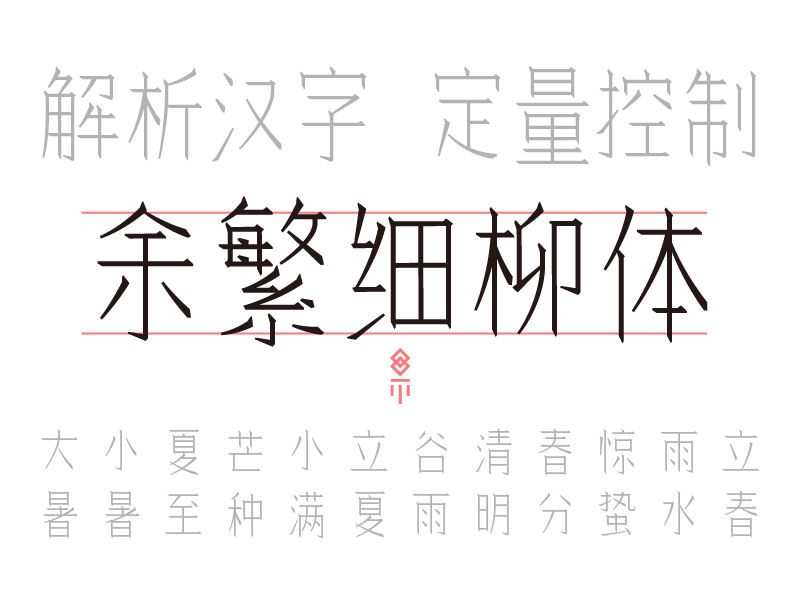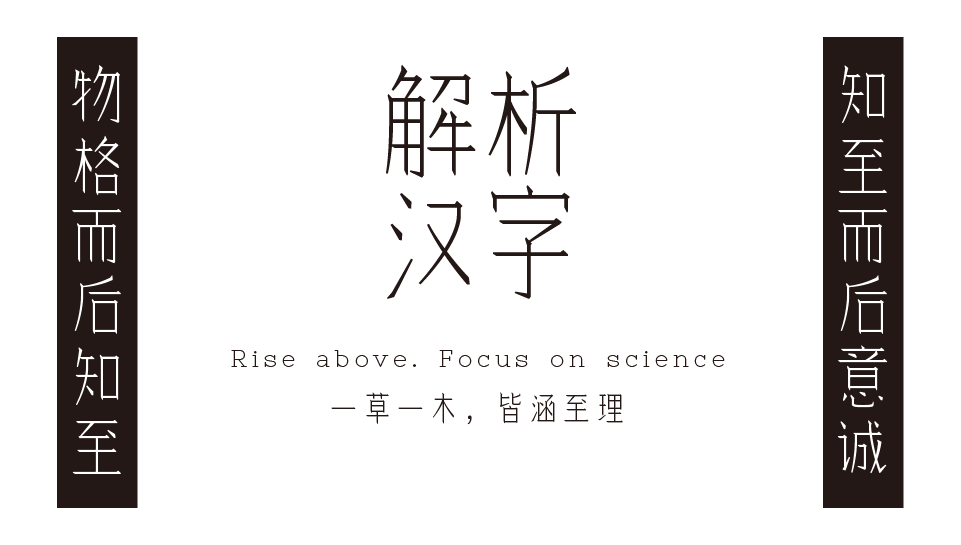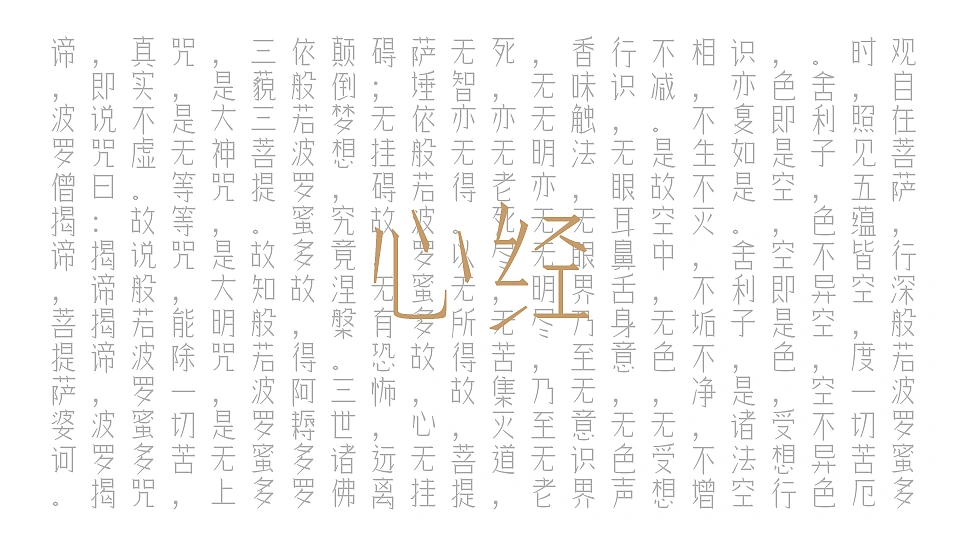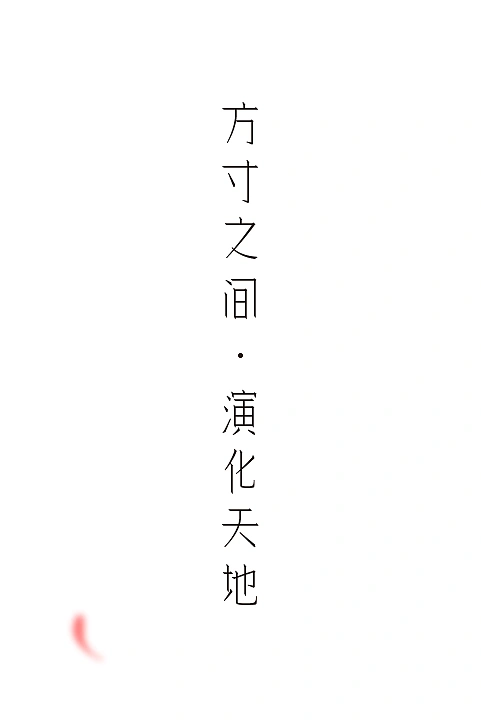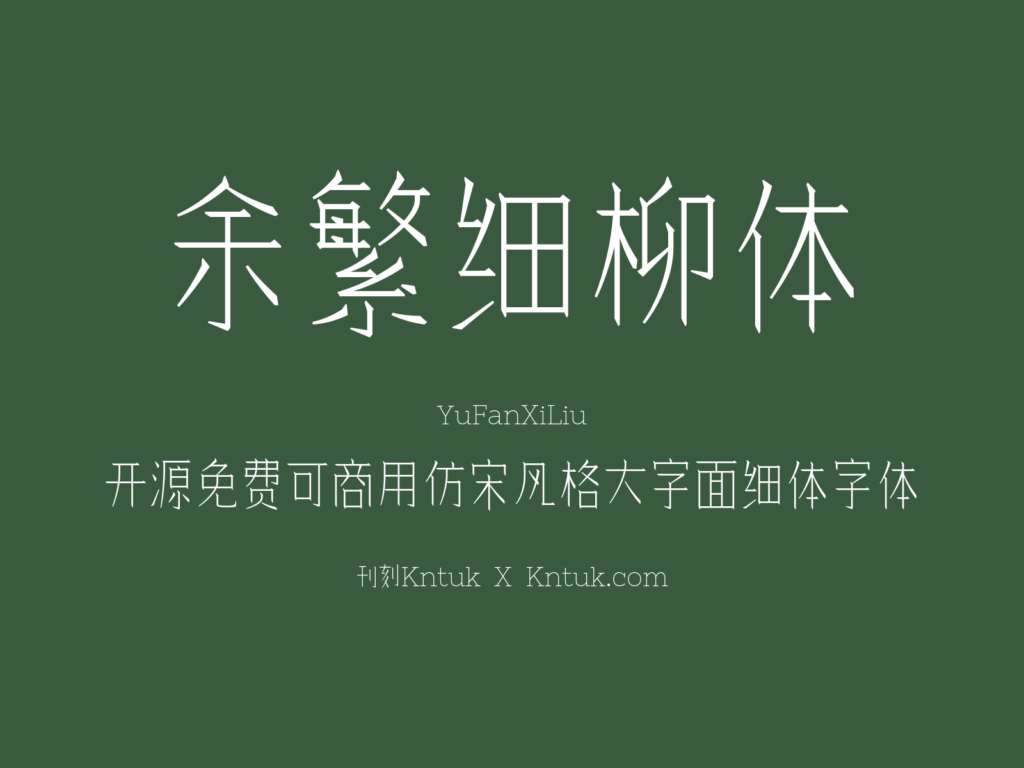
余繁细柳体的汉字主体是由动态组字系统繁星自动拼装生成的。这套机制把基础笔画拆成零件,通过算法反复试错重组,才筛出目前的字形库。西文与标点直接沿用了Nixie One的设计,授权协议也统一按OFL标准执行,便于后续自由二次开发。整体来看,这是一款主打大字面结构的纤细字體,线条走势刻意保留仿宋体那种植入屏幕的挺拔感。不过因为笔触压得很薄,字高卡在32px时,单根笔画的实际厚度仅约1px。一旦强行用在更小的屏幕上,线条极易糊连或断碎,清晰度会直线下降,所以日常排版务必避开32px以下的字号。设计阶段不断试错拼搭确实挺有意思,可落到逐字校对的环节就相当消磨耐心。密密麻麻的字表挨个过,得死磕那些算法拼接产生的细微断层或生硬转折。毕竟它并非人手一笔一划雕琢的成品,而是程序逻辑推导出的结果,内部难免残留些结构不够圆润或笔画交代不清的问题,眼下可能还有没覆盖到的盲区。目前项目保持开源免费商用,既然大伙儿都能直接拿来做东西,要是你在实际使用中碰见字形长得不协调、或是偏旁衔接别扭的情况,随时去GitHub上提个issue说明就行。收集这些零碎的反馈再慢慢修补,能让整款字体的稳定性好很多。在这儿先谢谢大家愿意花时间帮忙挑错。